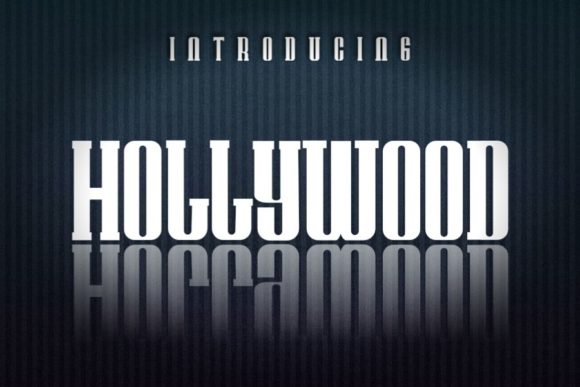
Hollywood - это высокий и фантазийный шрифт.
Независимо от темы, этот шрифт будет невероятно полезен в вашей библиотеке шрифтов, поскольку он способен возвысить любое творение.